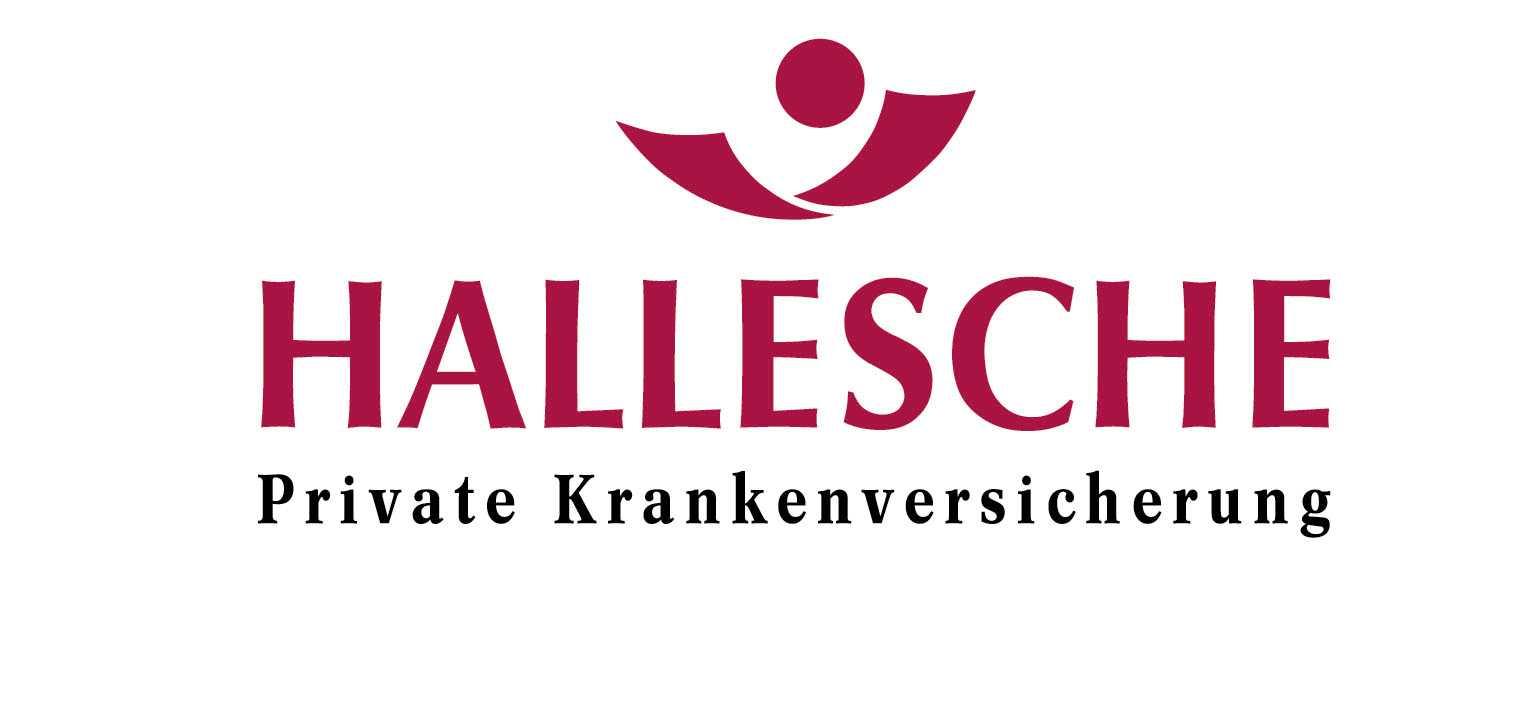
Font "Alte Leipziger" bzw. "Hallesche" Versicherungen gesucht
weiß jemand, welche Typo die Logos der Versicherungen "Alte Leipziger" oder "Hallesche" verwenden?
Ich finde gut daran, dass sie im Grunde grotesk ist, aber Serifen andeutet...
Suche den Original- oder ähnlichen Font. Darf auch was kosten.
Ich finde gut daran, dass sie im Grunde grotesk ist, aber Serifen andeutet...
Dann hast du bestimmt Vergnügen an dieser Liste: